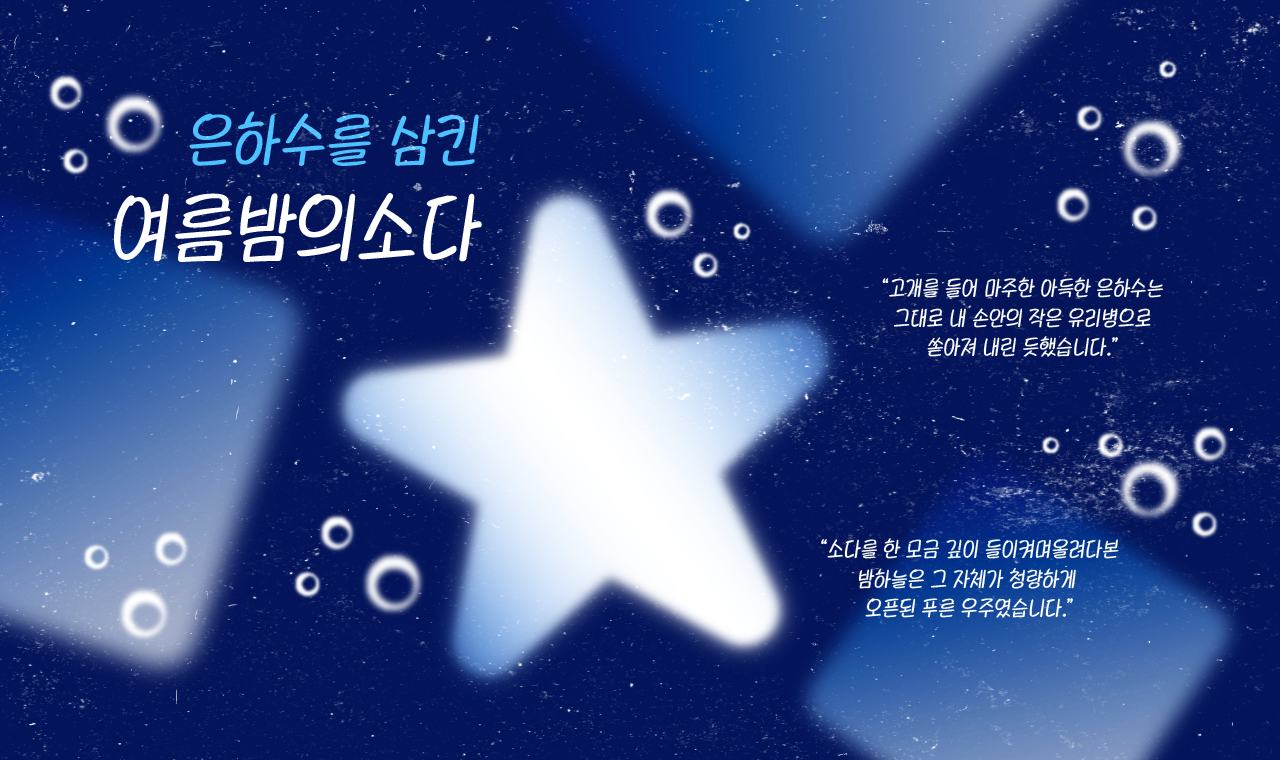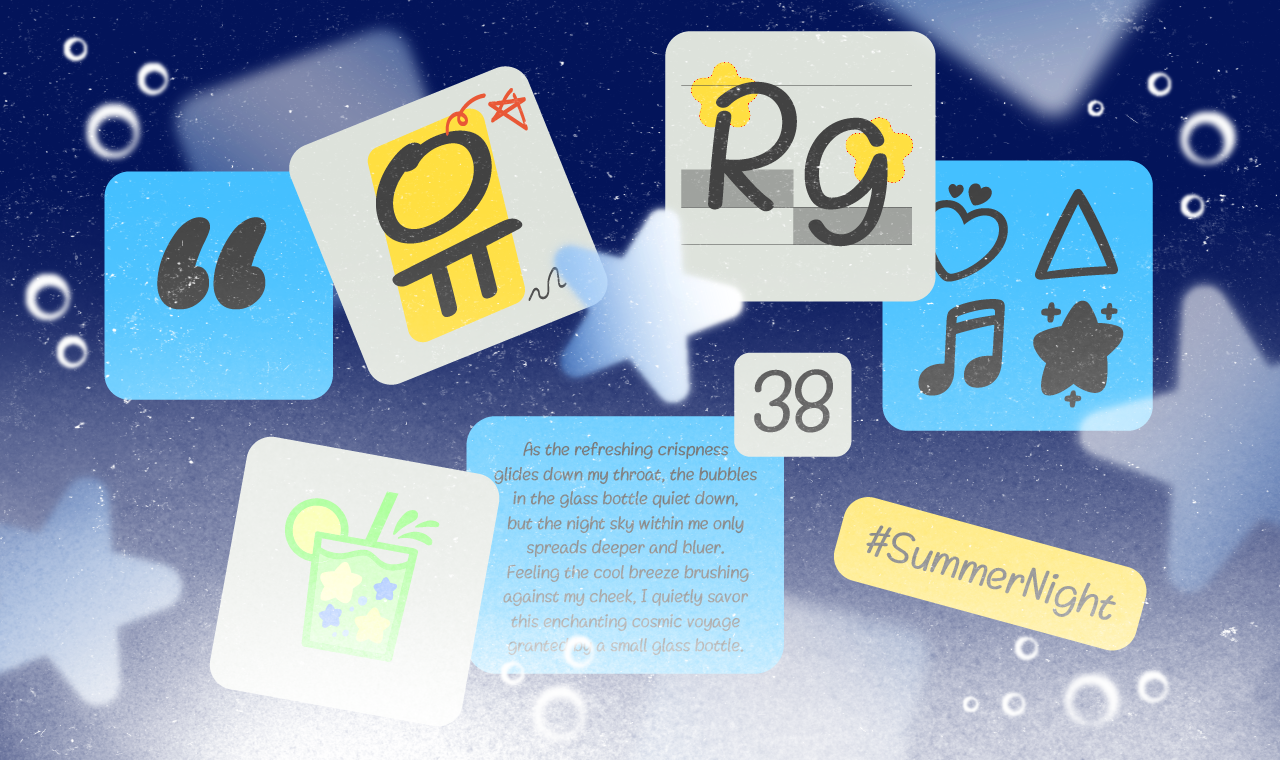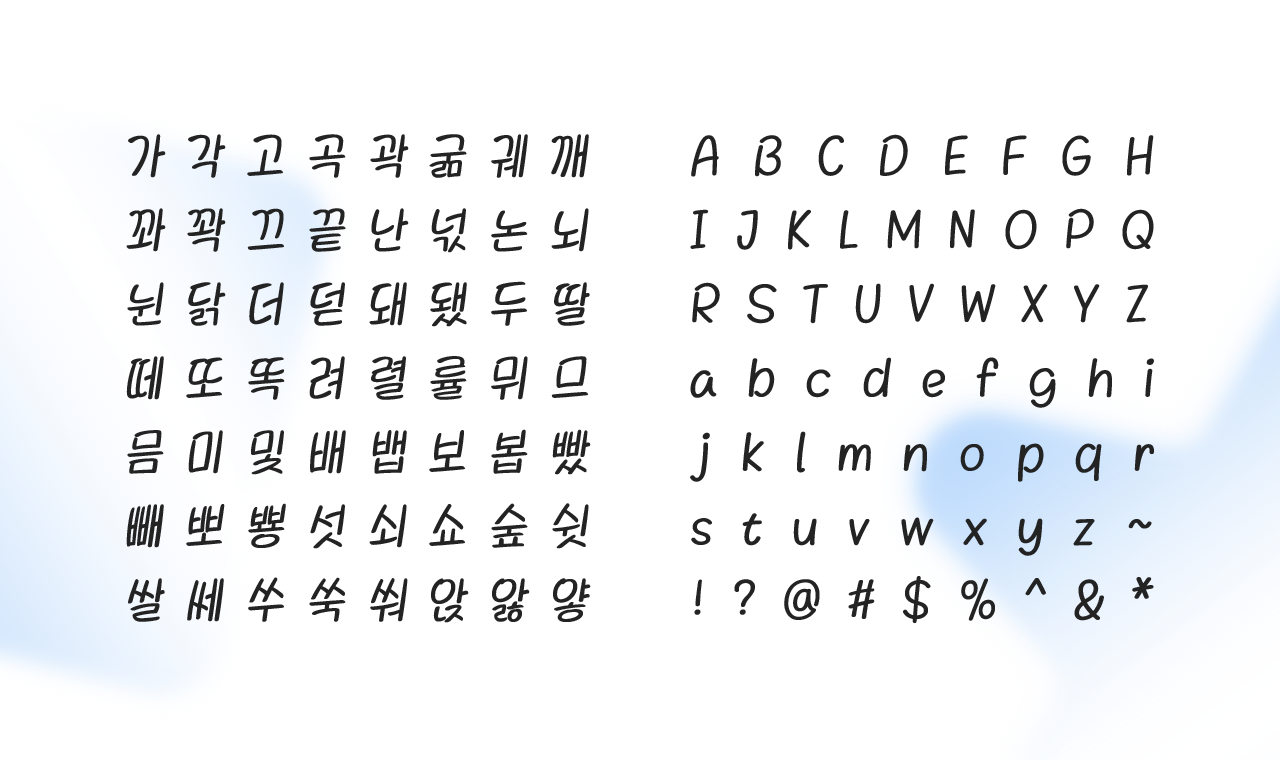
머리 위의 거대한 밤하늘을 한 모금 깊이 들이켜는 순간! 여름밤의소다는 다이어리에 꾹꾹 눌러 쓴 듯한 친근한 손글씨 구조 위에, 여름밤의 서늘하고 청량한 감성을 불어넣은 서체입니다. 친근하고 귀여운 필체 속에서 특히 돋보이는 동글동글하고 꽉 찬 ‘ㅇ’형태는, 마치 밤하늘에 몽글몽글 떠오른 은빛 기포나 소다 속 탄산처럼 싱그러운 생동감을 전합니다.일상의 기록에 청량함을 더해줄 ‘여름밤의소다’로 오늘 하루를 더 특별하게 기록해 보세요.
Yoon 여름밤의소다